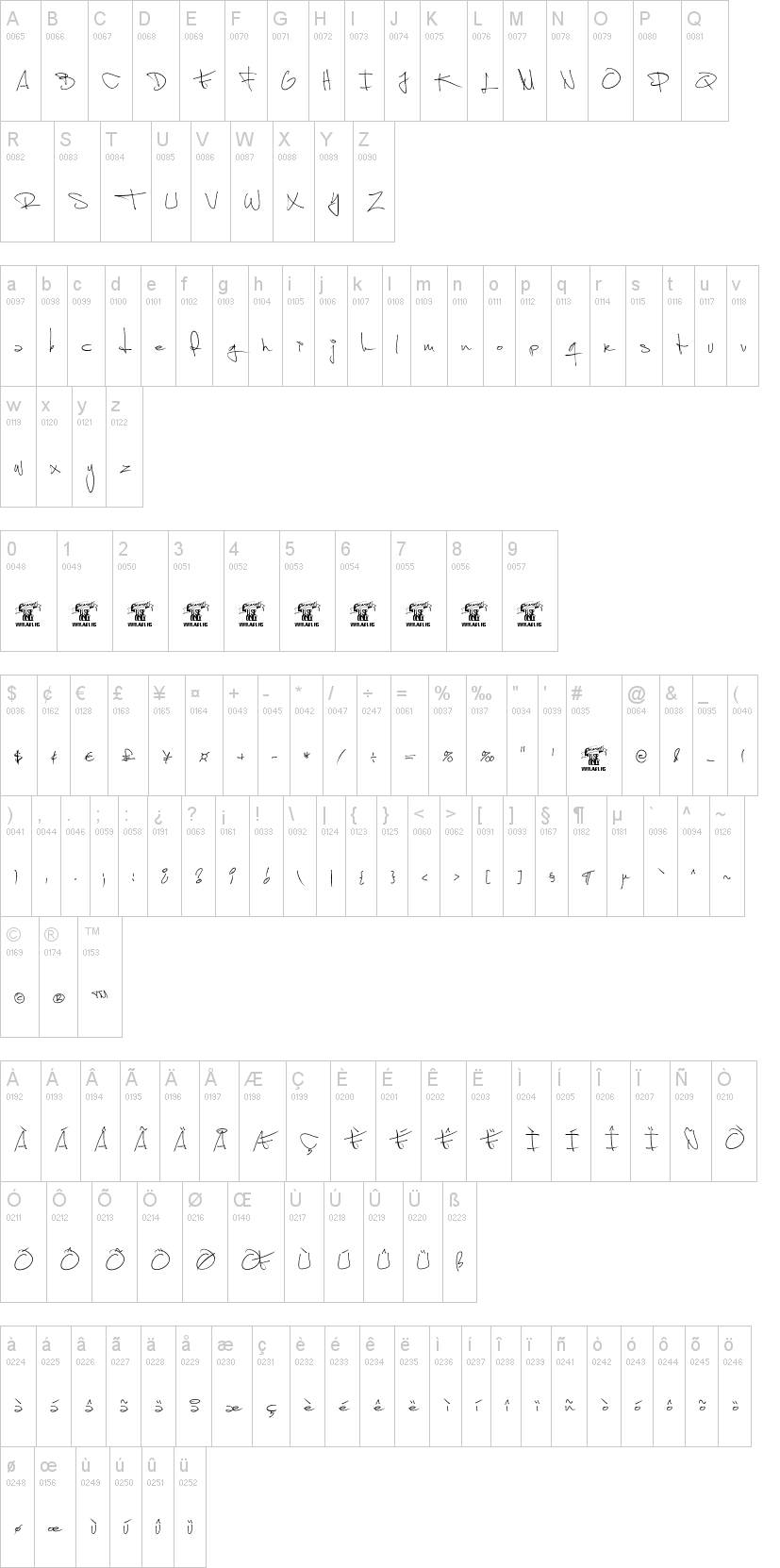
Shimes Two
Shimes Two是一款极具视觉冲击力的字体,它的设计灵感来自“艺术与科技”的结合,它具有现代感十足的外观,而且字体的每一个笔画都是精心设计的,从而让它看起来更加精致、细腻。它的字形比较细,但是又不失粗犷的感觉,而且它的字形也比较多样,可以满足不同的需求。此外,这种字体还具有良好的可读性,可以让文字看起来更加清晰、易读。
Shimes Two是一款非常不错的手写艺术字体,具有很好的视觉感,适合于文化类的宣传设计、商业类品牌的广告和产品包装设计以及个性化文字排版等较多场景。
Shimes Two字符映射图